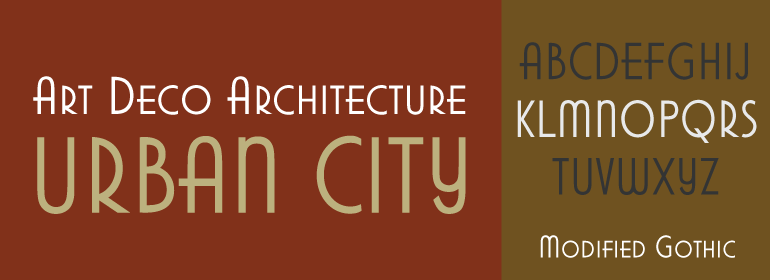
Modified Gothic™
Modified Gothic™,这款字体结构工整、笔画清晰,兼顾美观与易读性,适用于标题、正文、海报、包装、LOGO 等多种场景。字形优雅稳定,风格百搭耐看,适配日常排版与创意设计,让文字呈现更舒适、更具质感。Modified Gothic™一笔一画,皆是细节,以均衡的比例、流畅的线条打造舒适视觉体验,字形端正大气,风格简约现代。无论是商业设计、品牌宣传还是日常排版,都能轻松驾驭,让文字更有格调与力量。Modified Gothic™字体下载。
字体品牌: Linotype(Monotype) 设计师:Linotype Design Studio 字体分类:衬线体 字体属性:外文 字符集:Unicode 发布时间: 2018